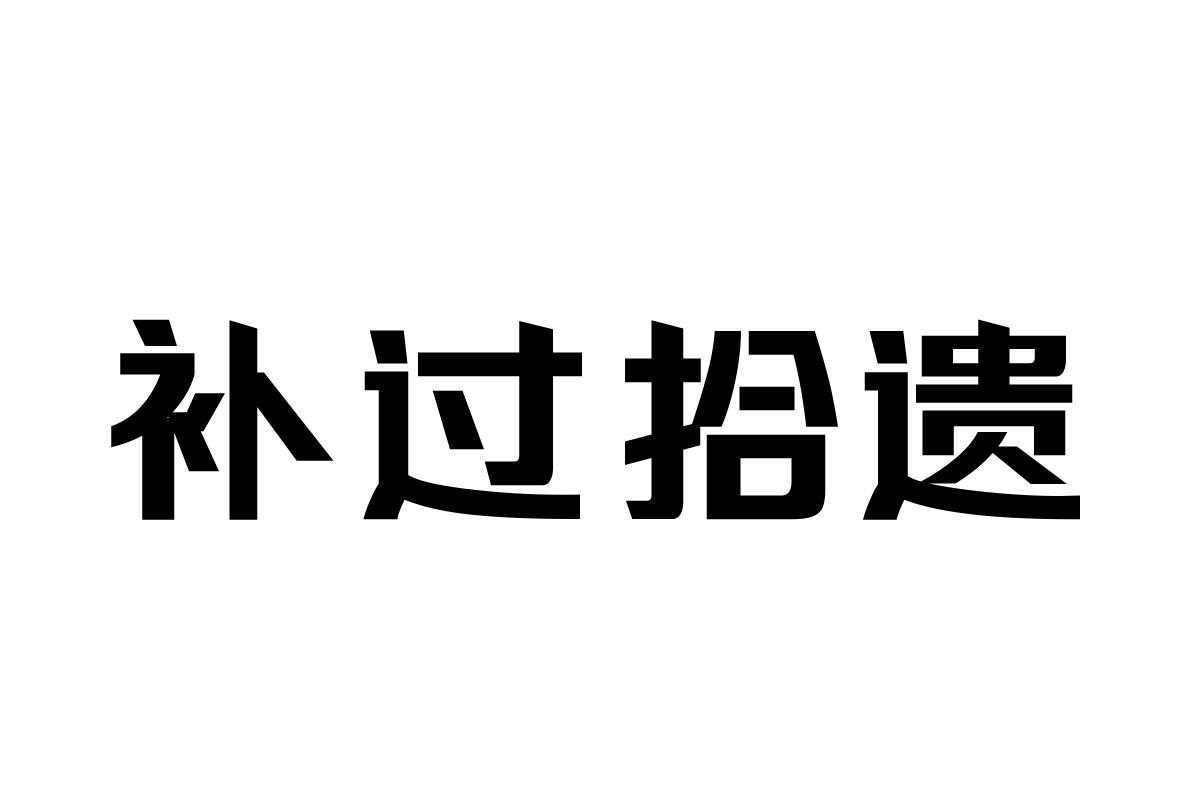
三极力量酷黑粗字体是一种具有强烈视觉冲击力的字体,其特点是笔画粗壮、结构紧凑。这种字体通常用于标题、广告和标识等场合,能够迅速吸引人们的注意力,传达出强烈的品牌或产品信息。
三极力量酷黑粗字体的特点如下:
1. 笔画粗壮:这种字体的笔画线条较为粗犷,给人一种力量感和动感,适合表达强烈的情感和态度。
2. 结构紧凑:虽然笔画粗壮,但整体结构仍然保持一定的紧密性,使得整个字体看起来更加协调和美观。
3. 易于识别:由于笔画粗壮和结构紧凑,这种字体具有较高的辨识度,便于人们在远距离或不同角度观察时也能迅速识别。
4. 适用范围广泛:三极力量酷黑粗字体适用于各种场合,如广告、标识、海报、宣传册等,能够有效地传递信息并增强品牌形象。
总之,三极力量酷黑粗字体以其独特的风格和特点,为各种设计场景提供了一种强有力的视觉表达方式。